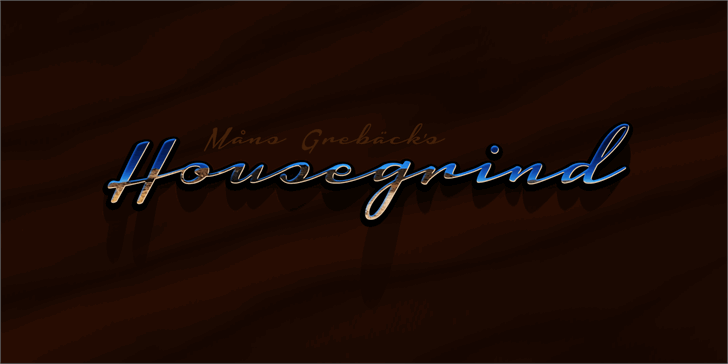
A Housegrind é uma fonte script criada pelo designer Hamilton que traz a essência delicada e elegante do artesanato manual, ideal para criar designs suaves e envolventes. Com linhas sutis e um acabamento cuidadosamente pensado, esta fonte se destaca como o elemento perfeito para uma variedade de projetos tipográficos, seja para embalagens de cosméticos delicadas ou letras digitais de livros de receitas casuais. Com sua natureza fluida e desenhada por um mestre do design gráfico, a Housegrind oferece um conjunto completo de opções para criar mensagens que se destacam ao longo da superfície. Seja você um criador digital buscando dar vida aos seus projetos digitais ou alguém interessado em adicionar um toque delicado a suas criações impressas, a Housegrind é uma fonte não apenas incrivelmente útil, mas também divertida para usar. Se você está planejando criar design gráfico profissional usando esta fonte, visite o site do designer para obter detalhes sobre como adquirir um licenciamento comercial. A Housegrind não só é versátil e elegante, mas também uma escolha irresistível para designers em busca de algo novo e inspirador no seu arsenal tipográfico.